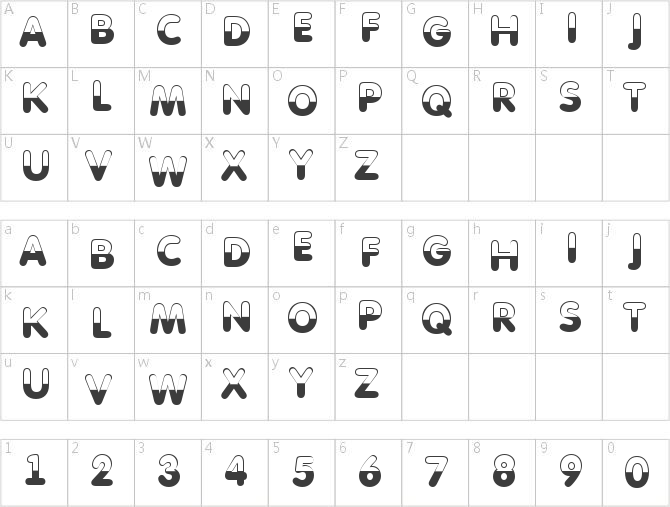
a_FuturaRoundTitulB-W-Bold 詳情頁
a_FuturaRoundTitulB-W-Bold字體字庫是一款讓人賞心悅目、百看不厭的英文字體,適合各類廣告和產(chǎn)品包裝設(shè)計(jì)應(yīng)用,字體大小0.07MB,格式為ttf字體,上傳用戶是82年的拉菲,作者/版權(quán)方為未知